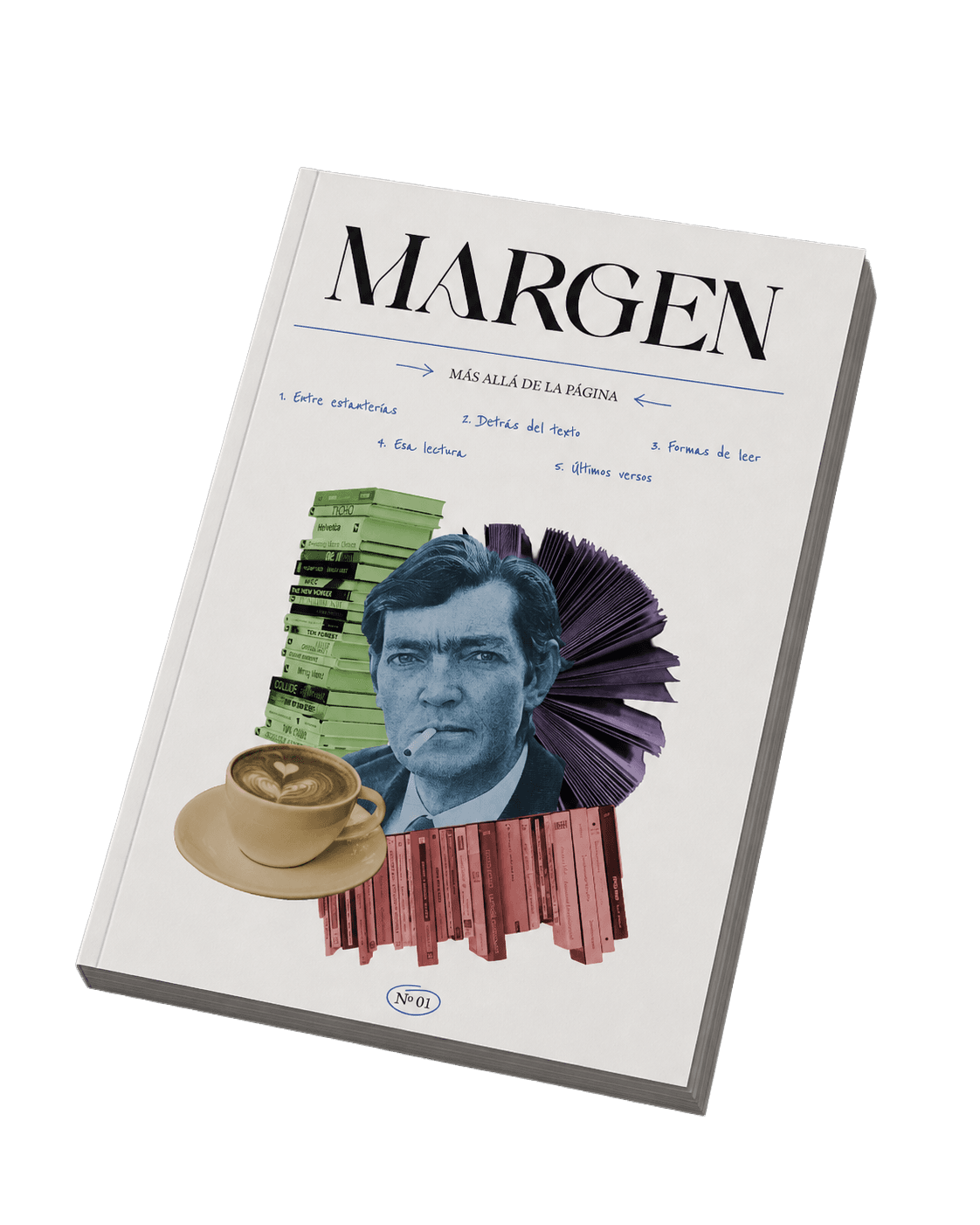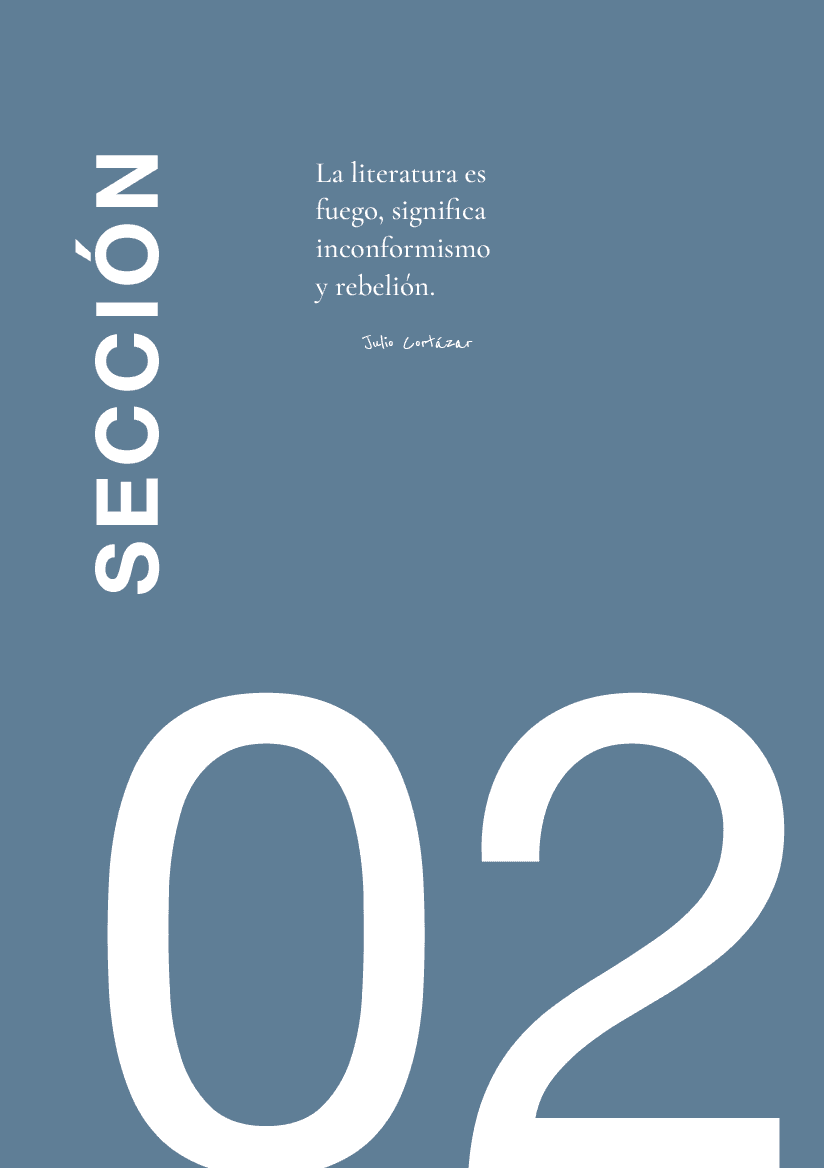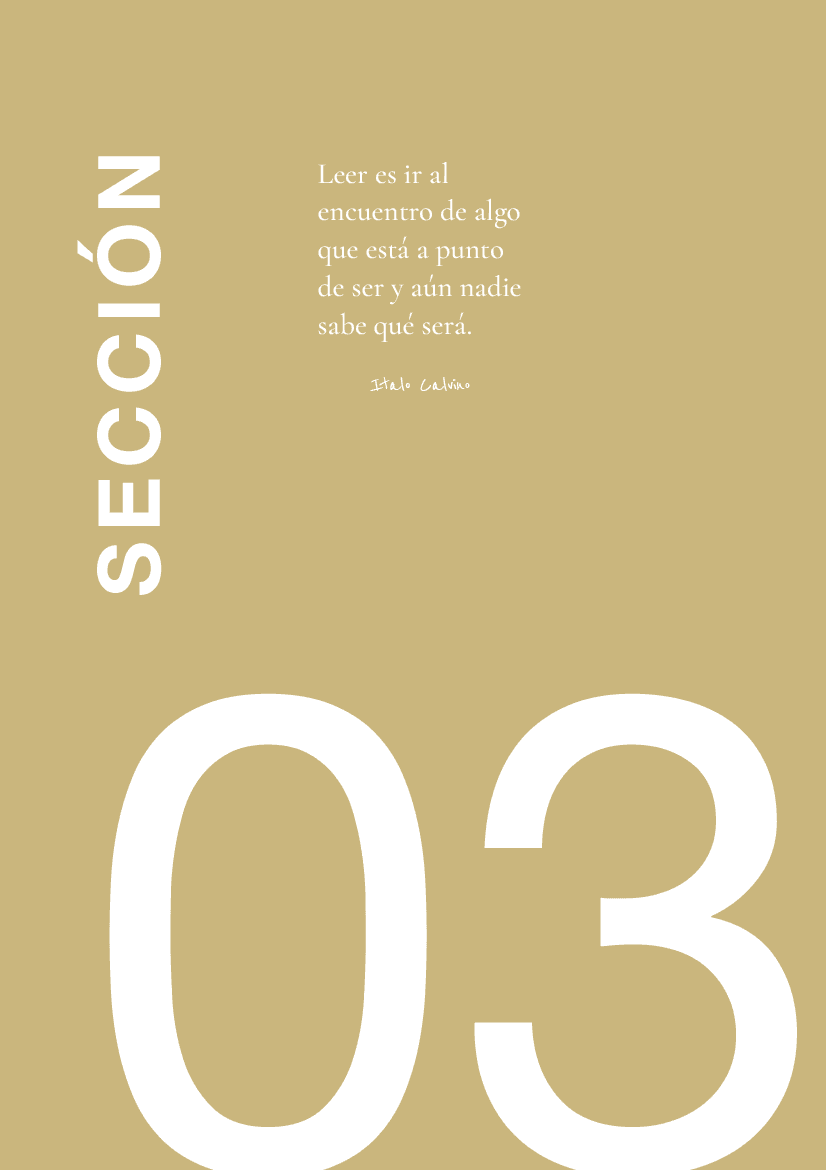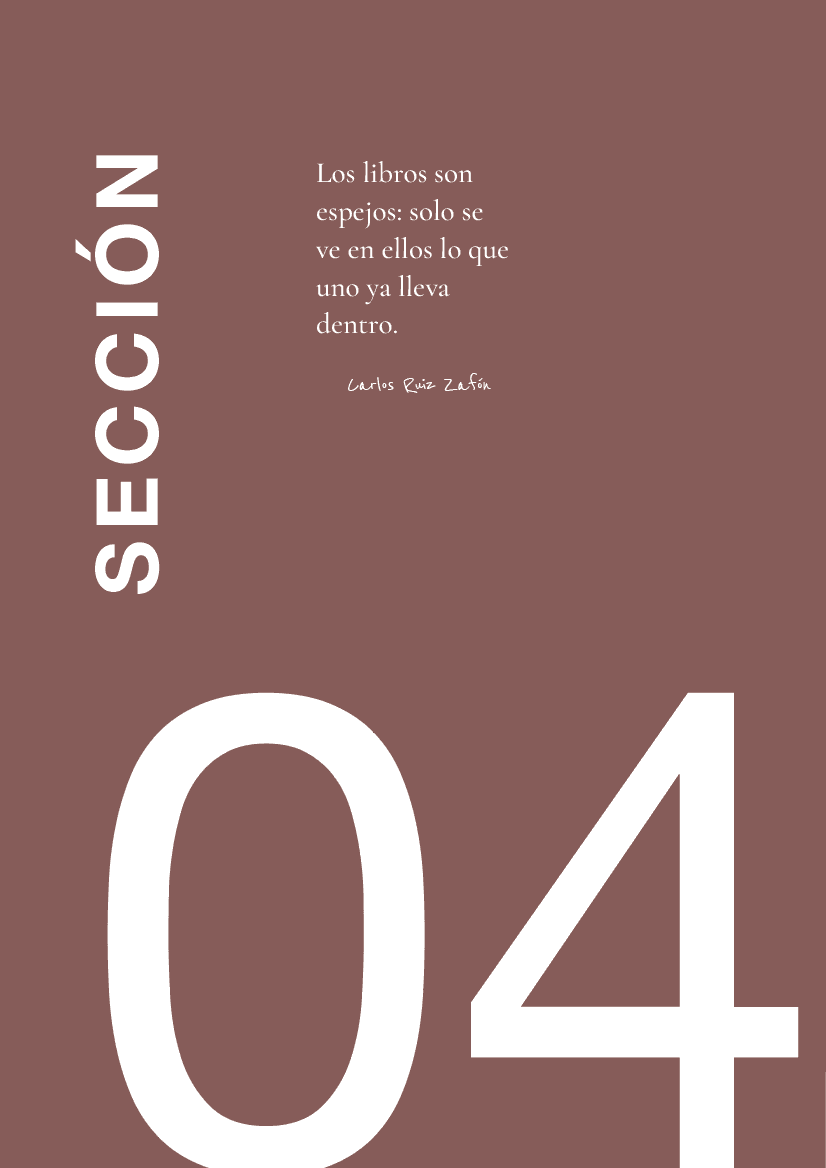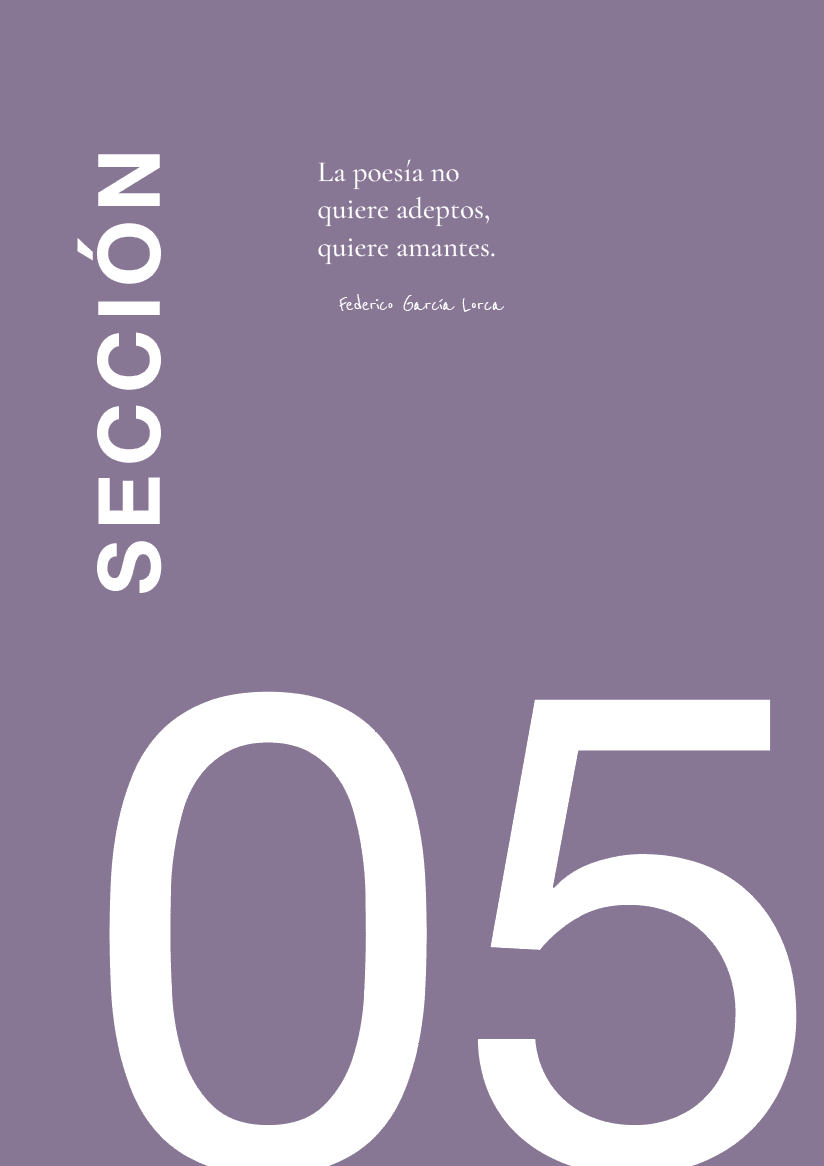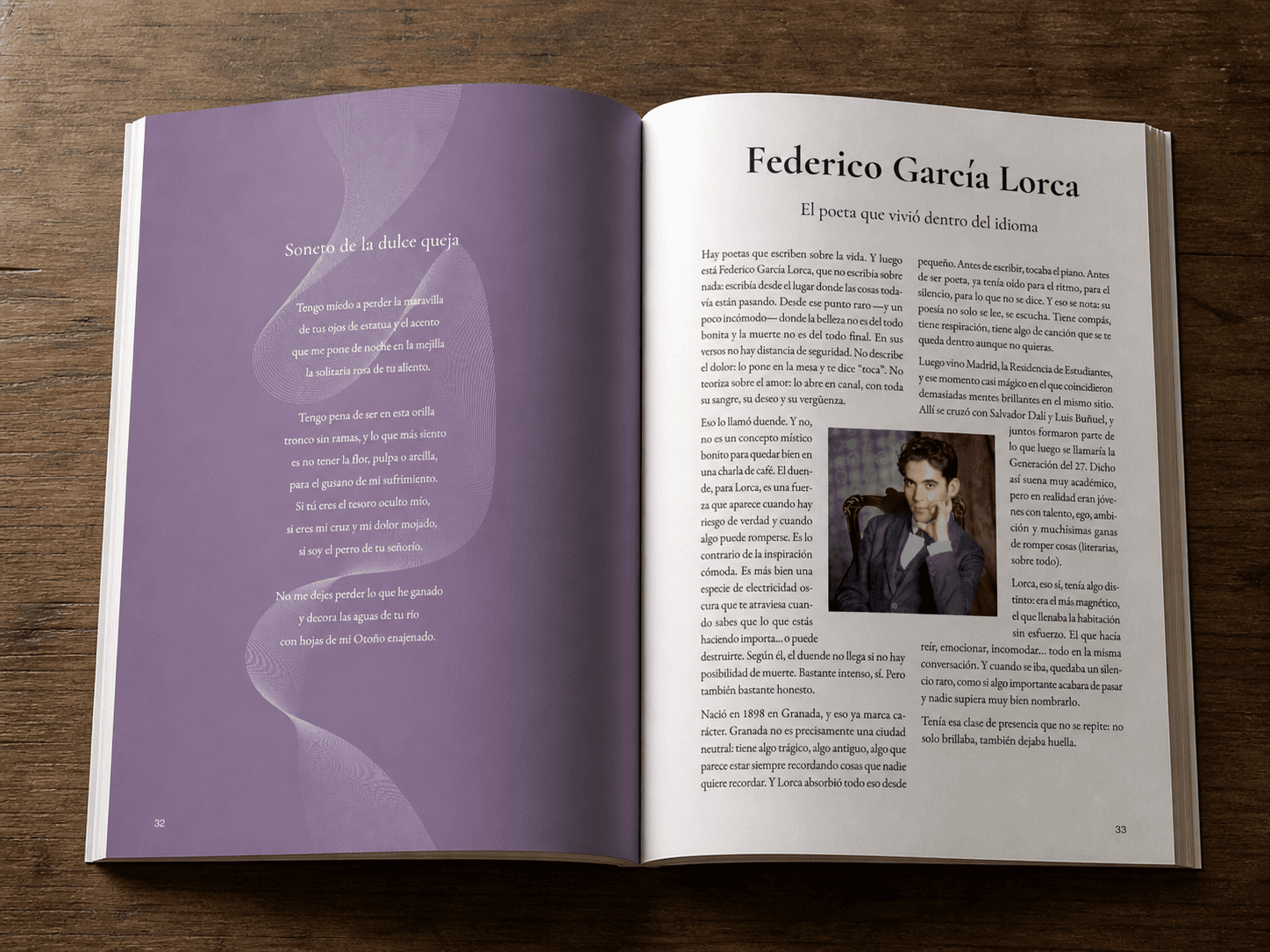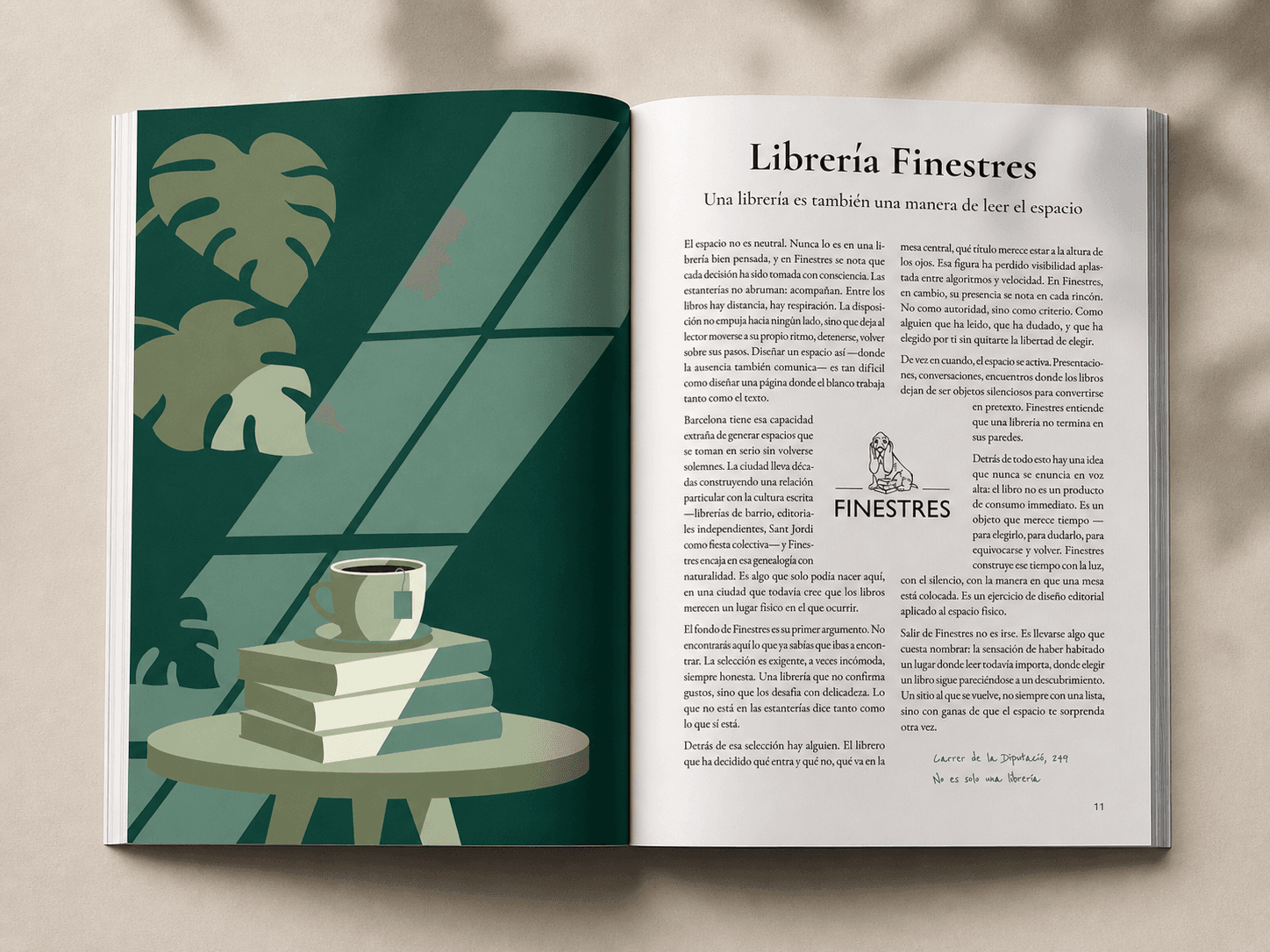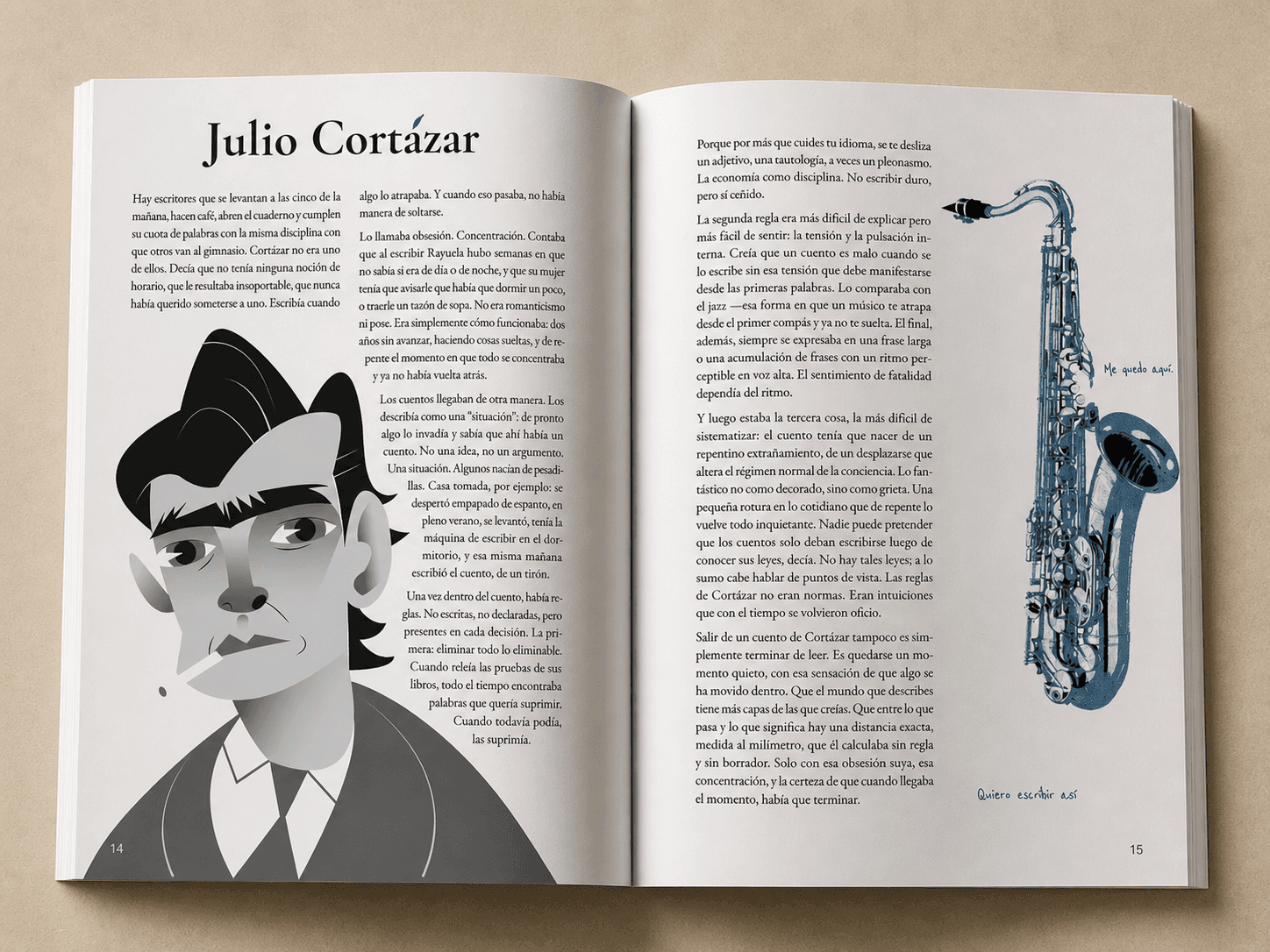
MARGEN es un proyecto de diseño editorial y maquetación de una revista cultural centrada en la experiencia de la lectura.
Desarrollo completo de identidad visual, sistema tipográfico, retícula, páginas maestras, ilustración vectorial en Illustrator, composiciones en Photoshop y arte final en Adobe InDesign.
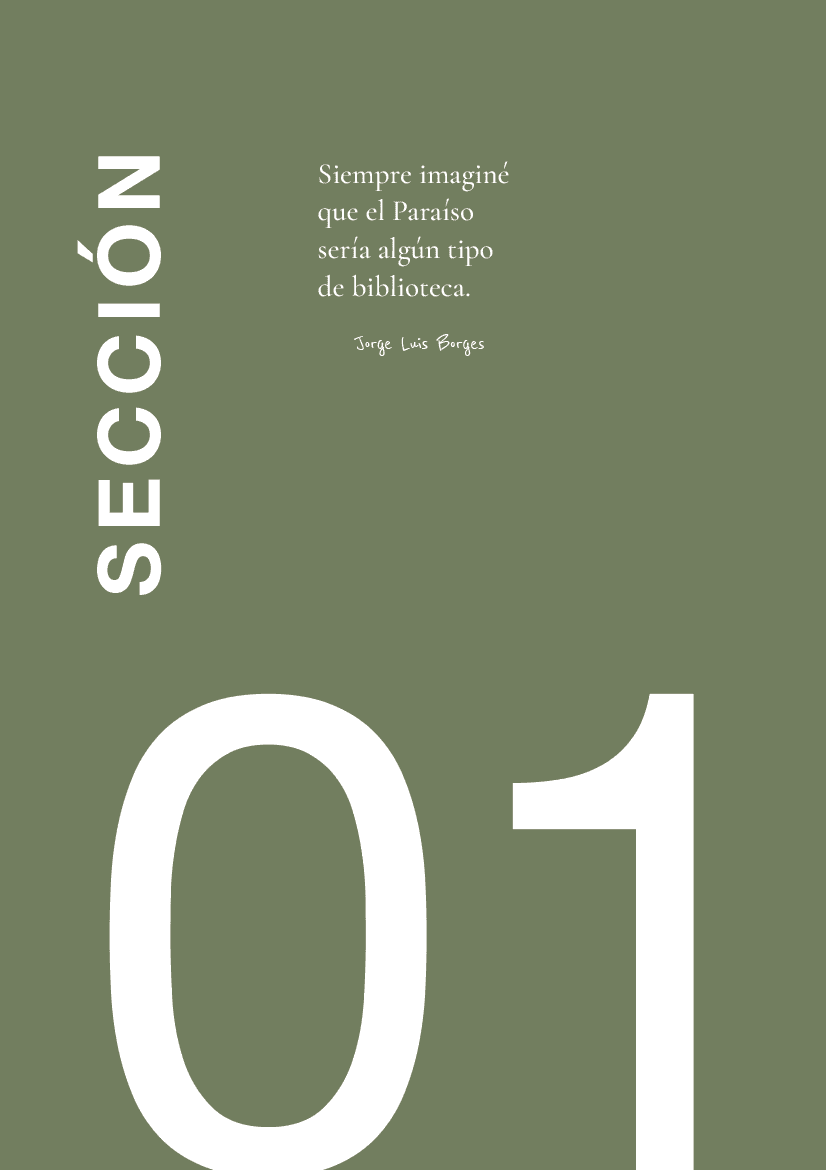
Desafío
Diseñar una revista cultural capaz de abordar la literatura desde una perspectiva contemporánea, alejándose de formatos rígidos o excesivamente académicos. El reto consistía en construir una publicación visualmente atractiva, con identidad propia y equilibrio entre contenido textual, legibilidad y recursos gráficos.
Solución
Se desarrolló una identidad editorial basada en una estética limpia y pausada, apoyada en una jerarquía tipográfica clara, una retícula flexible y una paleta cromática coherente. La revista combina maquetación cuidada, ilustración vectorial, composiciones fotográficas y anotaciones manuscritas para reforzar la idea de la lectura como experiencia cercana y personal.
Resultado
El resultado es una revista cultural con una identidad visual sólida y reconocible, capaz de integrar contenido literario y diseño editorial de forma natural. El proyecto demuestra capacidad para conceptualizar, estructurar y ejecutar una publicación completa, desarrollando un sistema gráfico aplicable a futuras ediciones.